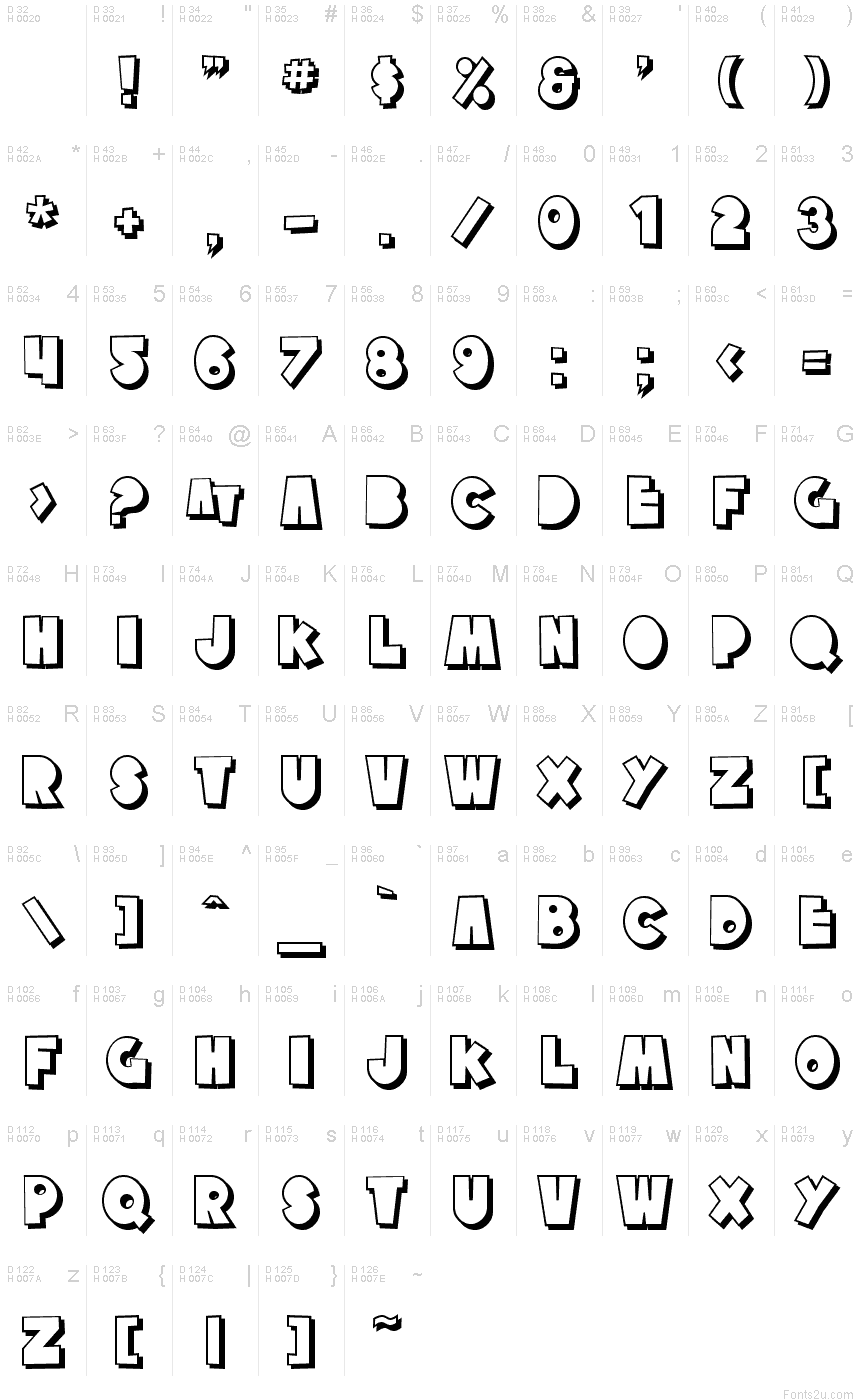
SF Tattle Tales Shadow von ShyFoundry ist eine kostenlose Comic-Display-Schrift mit einer energiegeladenen, fröhlichen Ausstrahlung. Die Buchstaben sind kräftig und verspielt; sie bestehen aus breiten Blockformen, die durch einen dicken, versetzten Schatten hervorgehoben werden, was der gesamten Schrift einen ausgestanzten, comic-artigen Look verleiht.
Sie passt perfekt zu Posterüberschriften, Kinderbuchcovern, comicartigen Titeln, Partyeinladungen und verspielten Verpackungen, bei denen die Worte eine große, einfache Wirkung brauchen. Diese kostenlose Schrift eignet sich auch hervorragend für kurze Bannertexte oder Monogramme, da der Schatteneffekt selbst wenigen Buchstaben genug Präsenz verleiht, um ein ganzes Layout zu tragen.
SF Tattle Tales Shadow